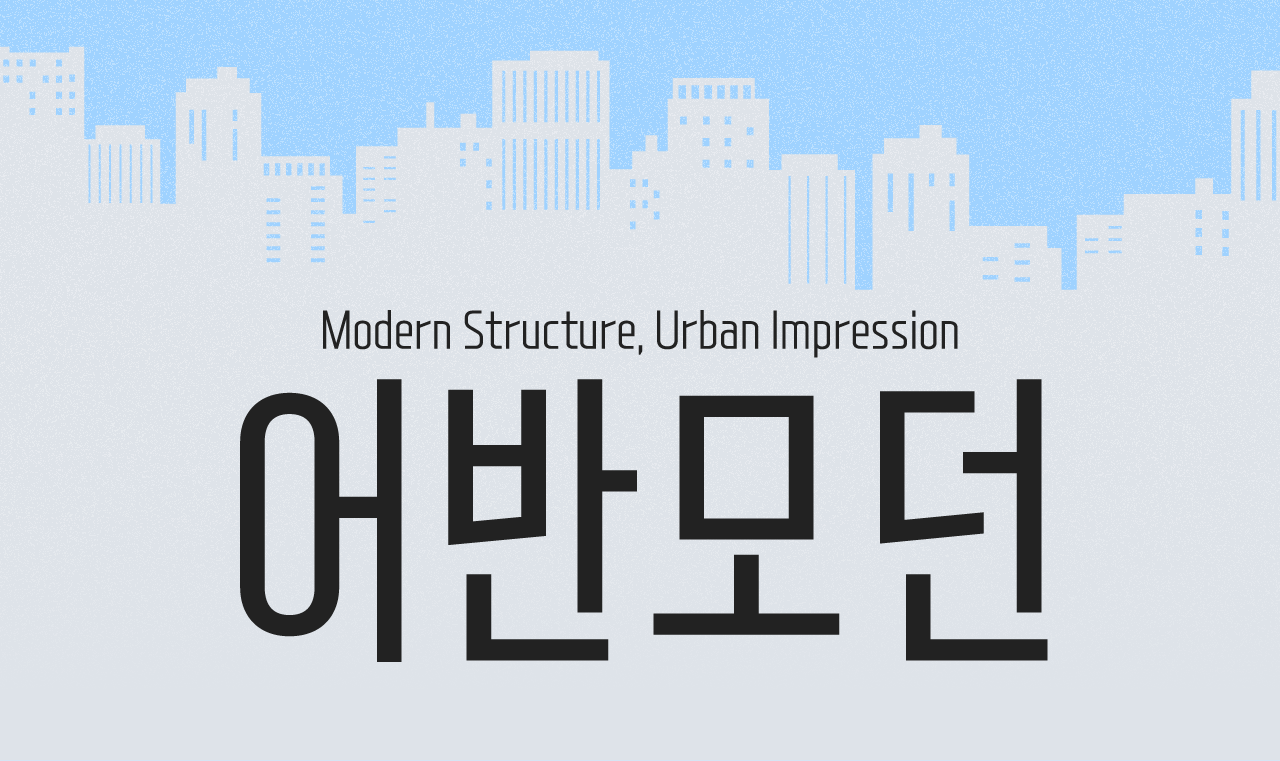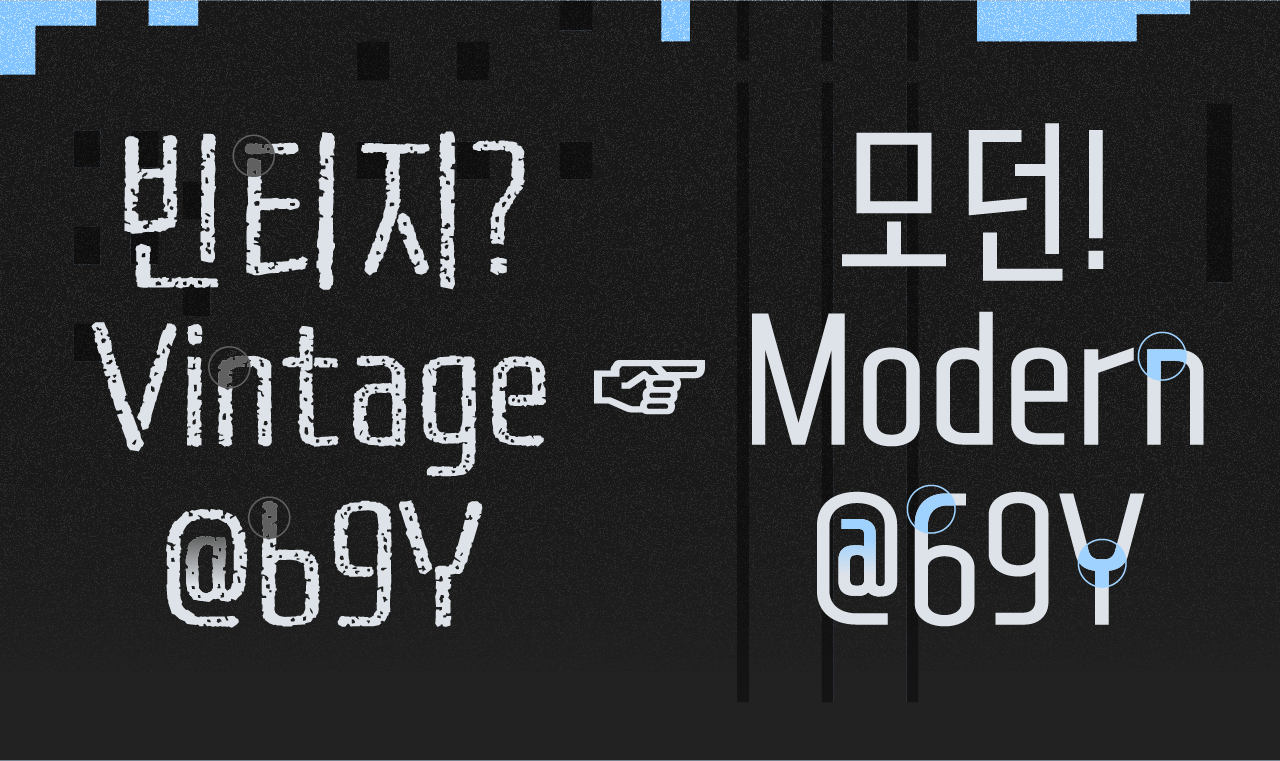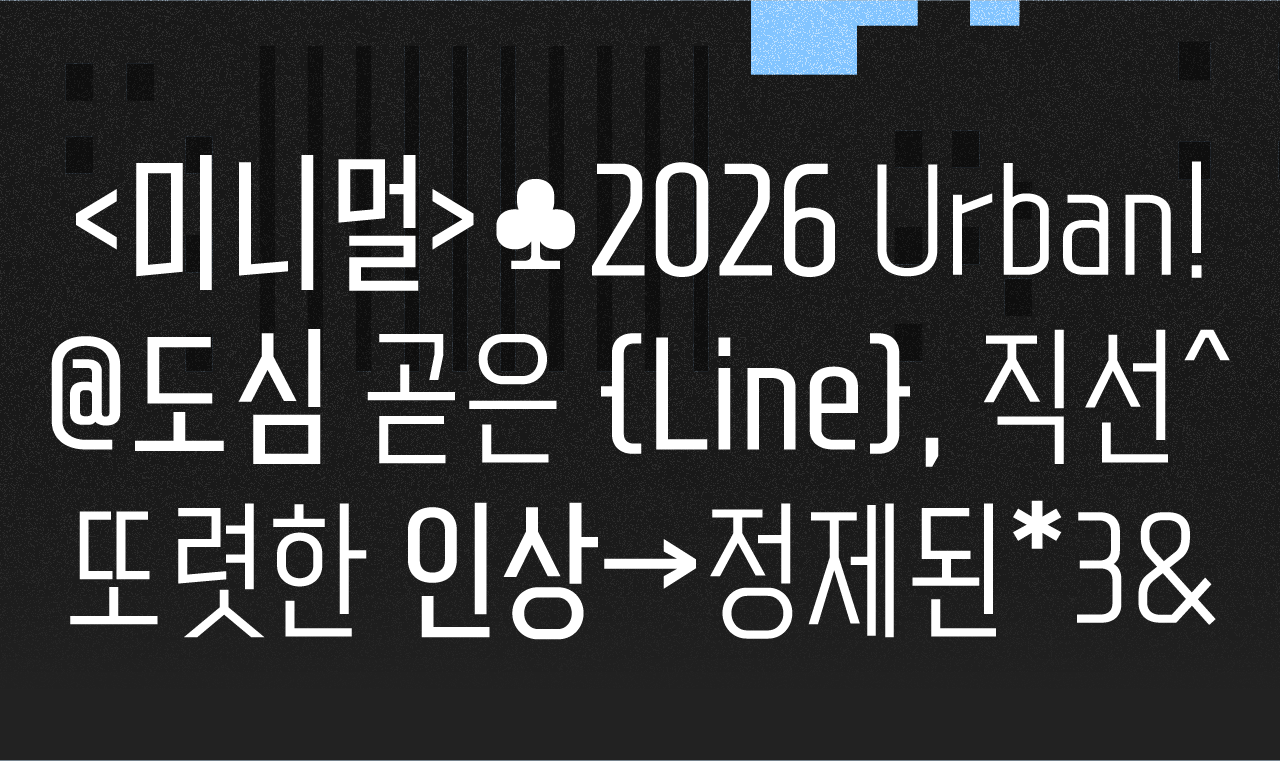
Yoon 어반모던은 기존 어반빈티지의 질감을 덜어내고, 보다 정제된 형태와 현대적인 감각으로 새롭게 완성한 서체입니다. 끊어져 있던 스텐실 구조를 자연스럽게 정리하고 자소 비율을 세심하게 조절해, 중립적이면서도 모던한 인상을 전합니다. 반듯한 선과 안정적인 비례가 만들어내는 또렷한 분위기는 메시지를 더욱 선명하게 드러냅니다. 어반모던으로 도시적이고 깔끔한 인상을 완성해 보세요.
Yoon 어반모던